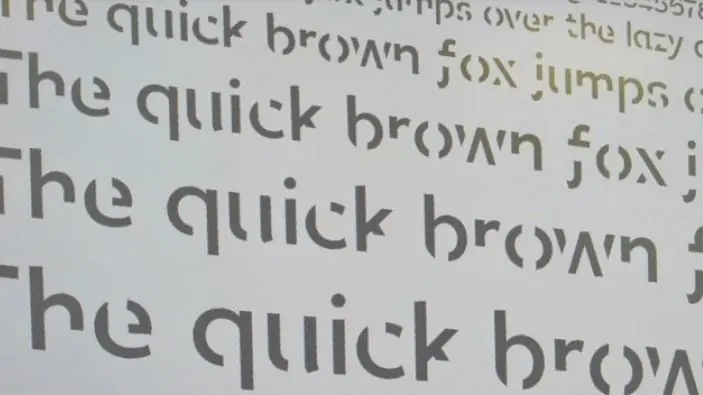
Tipografía científica diseñada para mejorar tu memoria
Ha tenido alguna vez para volver a leer el texto varias veces con el fin de comprender o memorizar, este problema es probablemente familiar para todos todos los estudiante.
Investigadores de la Universidad Royal Melbourne se han unido y tratado de resolver este problema. Paradójicamente, la mejor forma de memorización el texto leído es que sea difícil percibir la fuente. Los investigadores y los diseñadores han creado Sans Forgetica, y su característica principal es la ausencia de algunas partes de las letras como podemos ver en esta pagina web puedes verlo en línea y probarlo si funciona.(http://sansforgetica.onlinegratis.tv).
Tipografía científica diseñada para mejorar tu memoria
Según los autores, esta apariencia de los personajes anima al cerebro a participar en un estudio más profundo del texto y a memorizarlo mejor y parece que funciona. El cerebro, por supuesto, va a tratar descifrar la forma de símbolos, así que al hacer esto, se ralentizará la lectura, que posteriormente se mejora la memorización el método, de acuerdo con los resultados del experimento, realmente funciona.
Para probar la eficacia del estudio se realizó en el que participan 400 estudiantes que dividieron en dos grupos se cree que la fuente es útil en la preparación de los estudiantes para los exámenes. La versión final de la fuente fue creada sólo en el tercer.